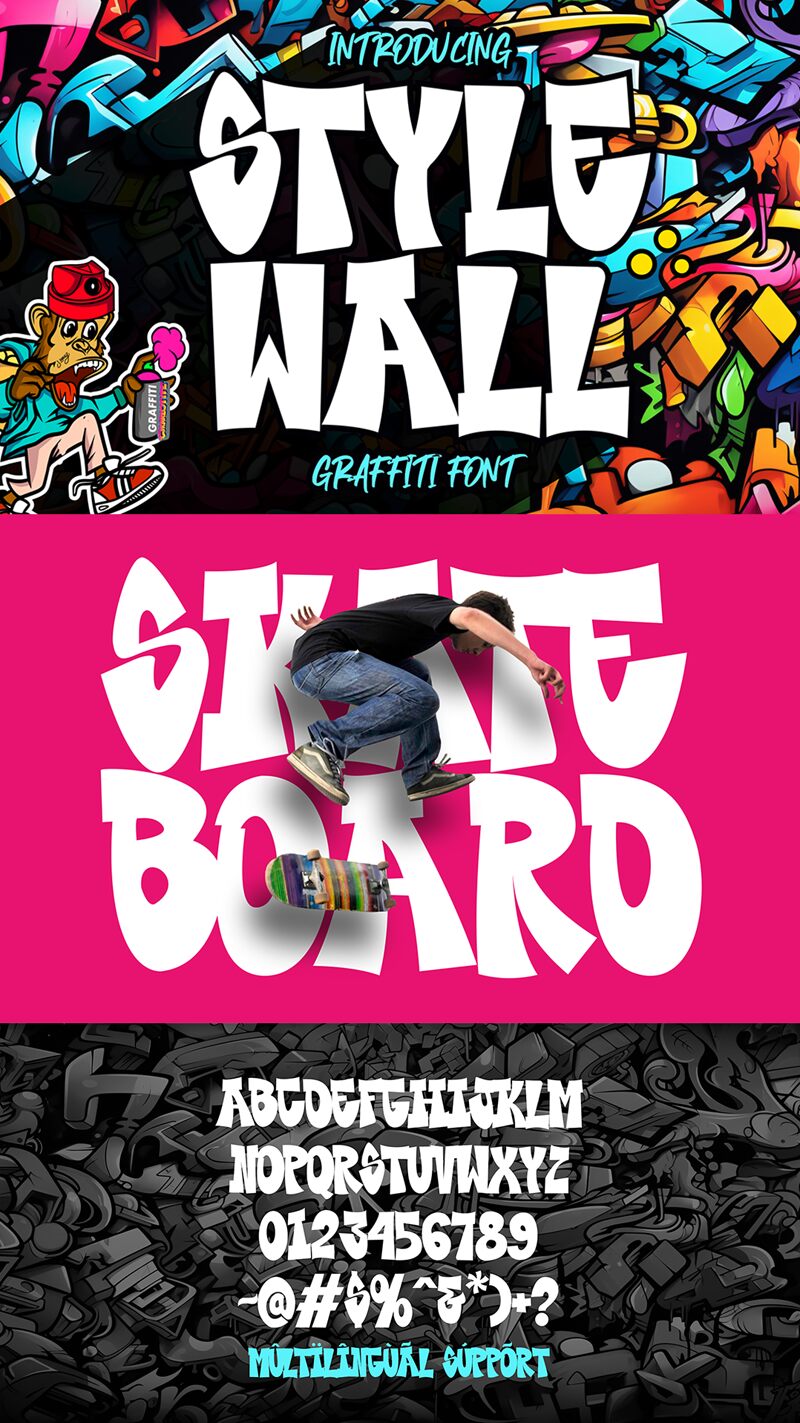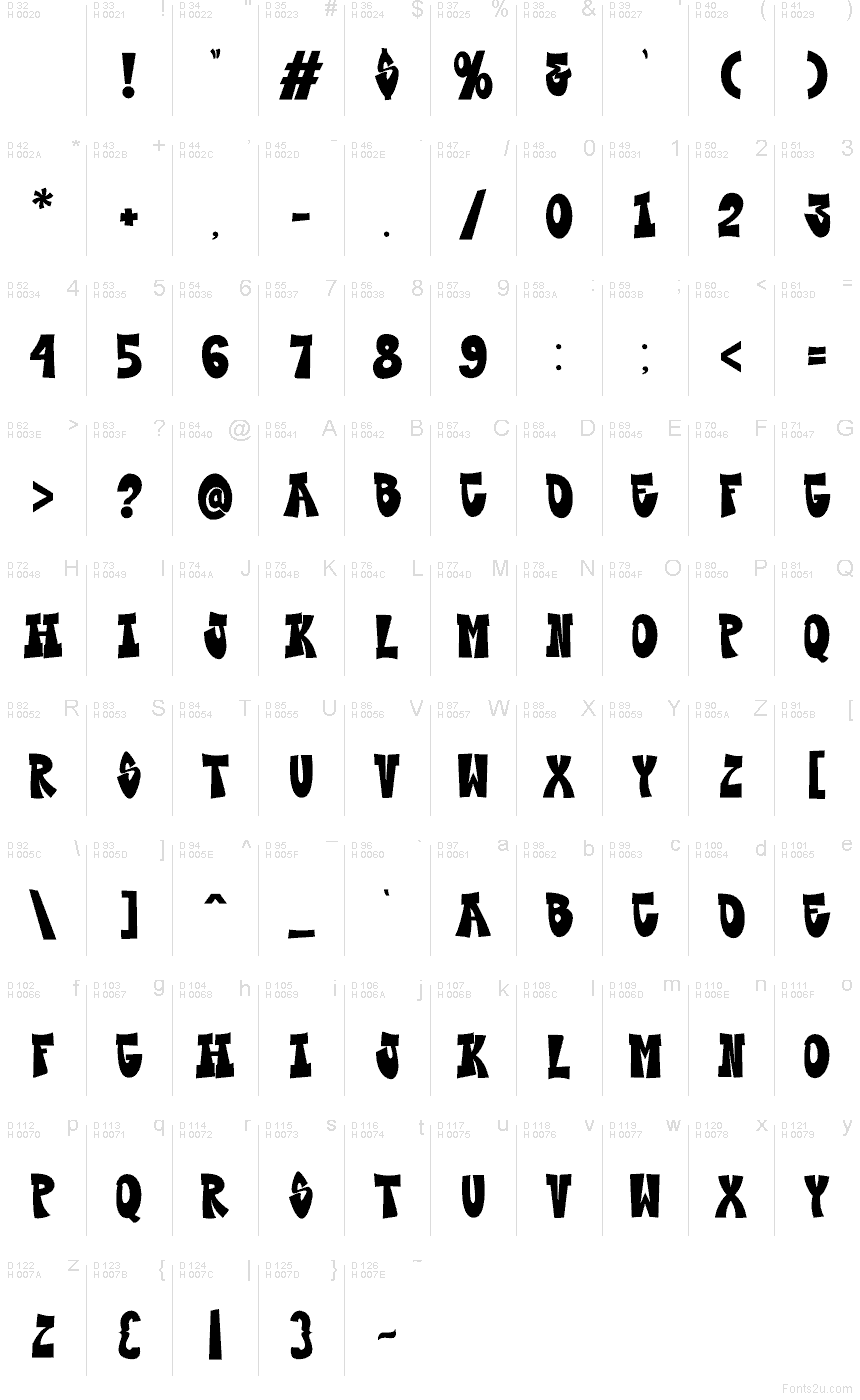
Style Wall od Cikareotype Studio je bezplatný graffiti font definovaný výraznými černými siluetami, které se naklánějí, rozpínají a zužují jako narychlo lepený papír na zdi. Nepravidelné horní hrany, sevřené spoje a nadměrné křivky dodávají písmu fyzický a uvolněný vzhled, který má blíže k ručně malovanému street-taggingu než k upjatému designu.
Tato syrová hmota dává krátkým textům hlasitou roli na hudebních letácích, grafikách pro skateboardy, nálepkách, streetwearovém brandingu a titulcích plakátů. Skvěle se hodí také pro náhledy videí a obaly alb, kde nevyrovnaný rytmus a kompaktní tvary dokážou zprostředkovat surový městský nádech, aniž by potřebovaly další dekorace.